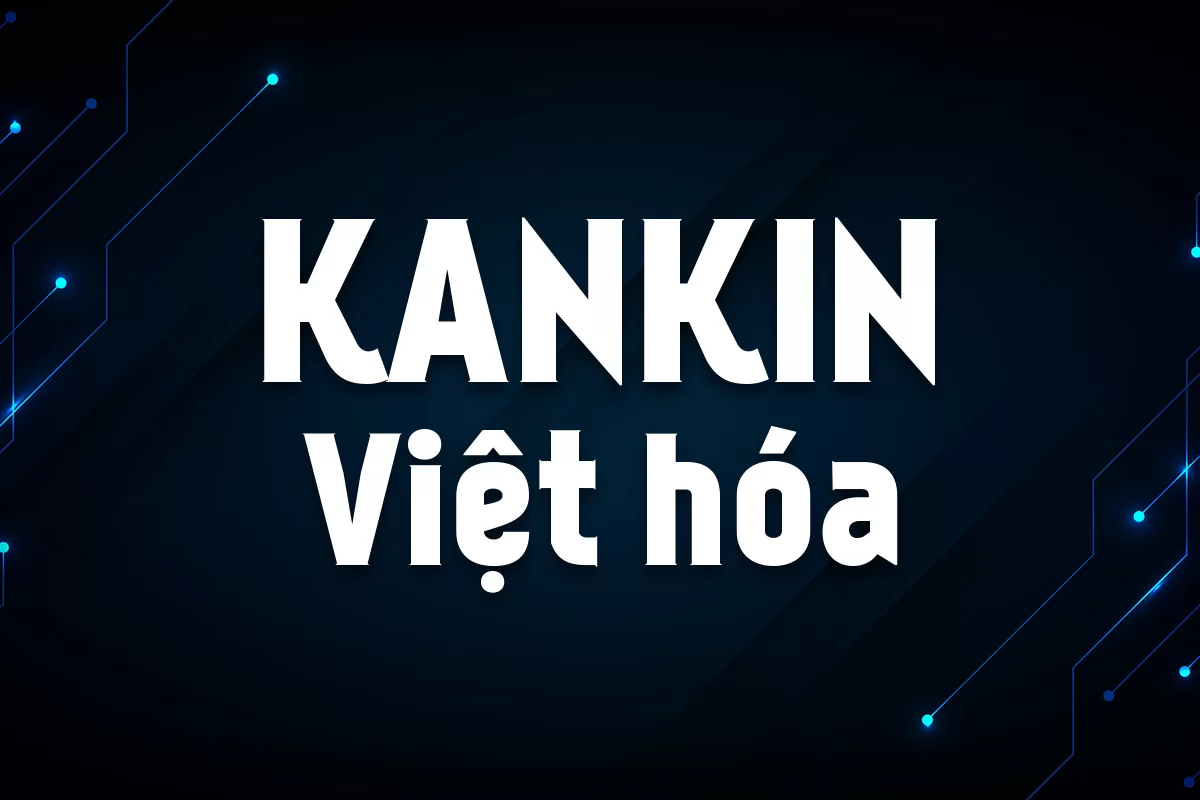
Kankin Việt hóa là một font sans-serif mang phong cách hiện đại, mạnh mẽ với các đường nét góc cạnh và dứt khoát. Thiết kế chữ cái vuông vức kết hợp với các chi tiết phá cách ở đầu hoặc chân chữ giúp Kankin trở nên nổi bật trong các dự án thiết kế công nghệ, game, tiêu đề poster hoặc giao diện ứng dụng. Font có độ dày cao, phù hợp với các tiêu đề lớn cần tạo điểm nhấn mạnh mẽ và rõ ràng. Phiên bản Việt hóa đã được tinh chỉnh tỉ mỉ để hỗ trợ đầy đủ dấu tiếng Việt, đảm bảo tính thẩm mỹ và nhất quán trong từng con chữ. Đây là lựa chọn hoàn hảo cho các nhà thiết kế đang tìm kiếm một kiểu chữ đậm chất tech, hiện đại và cá tính.